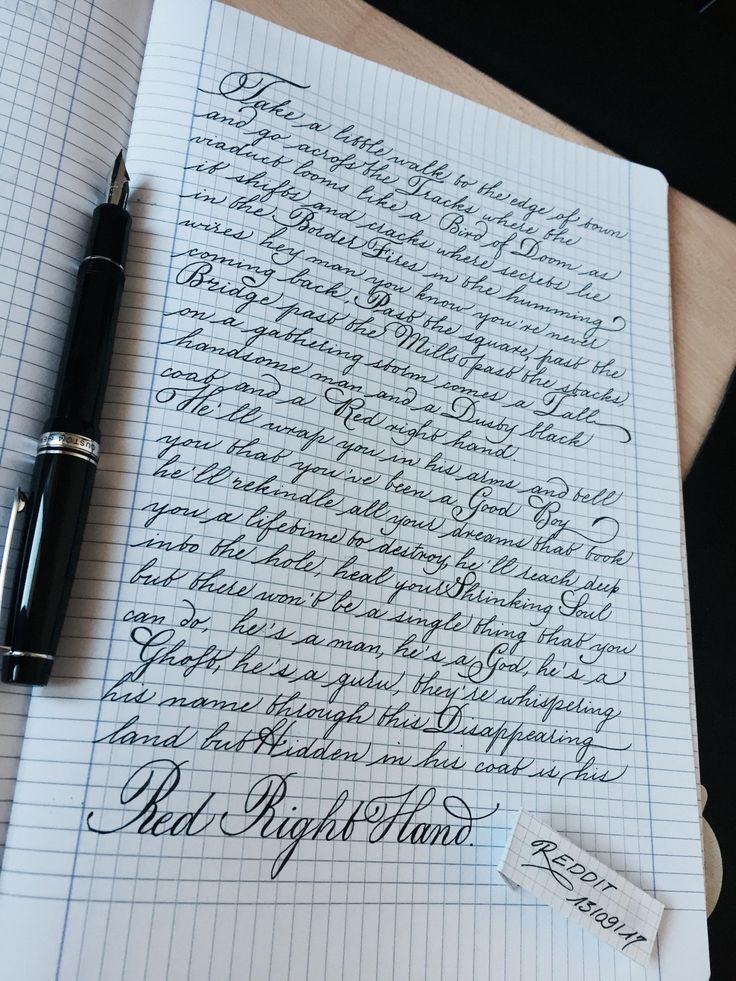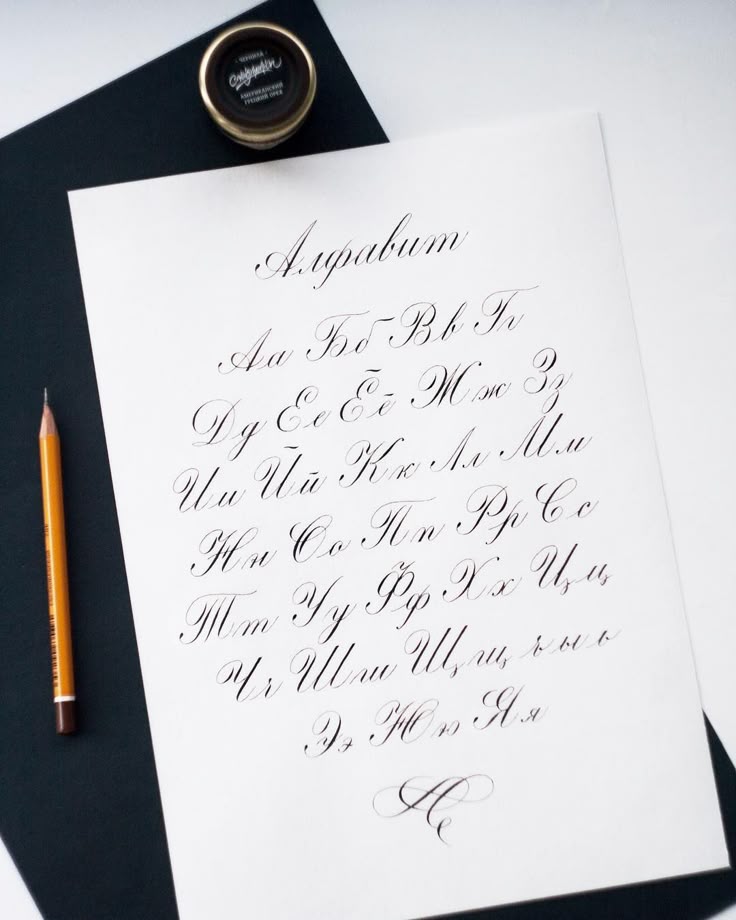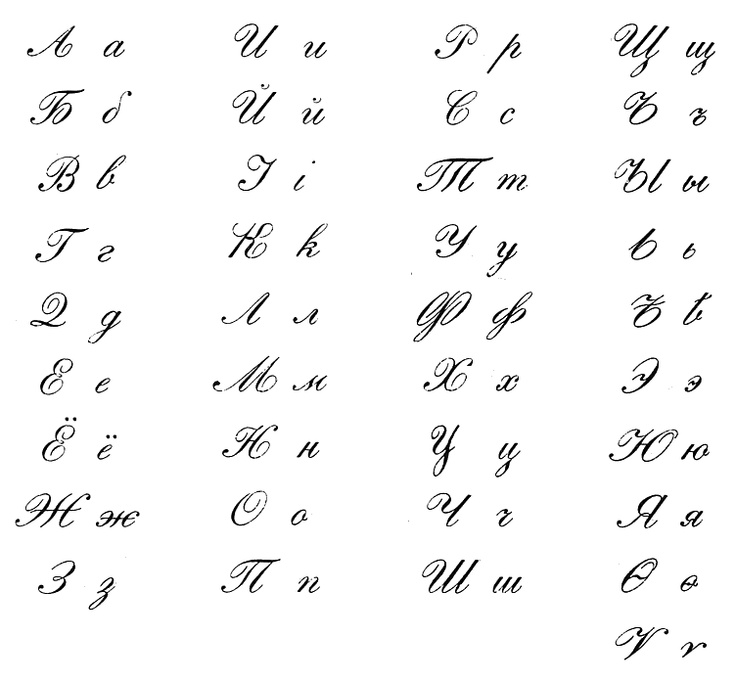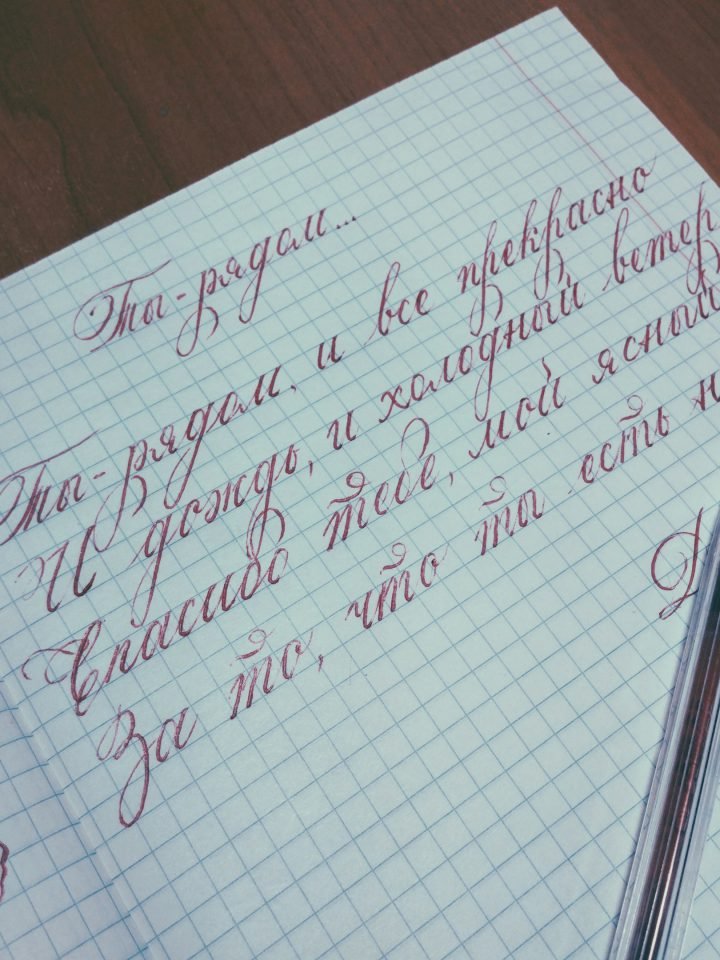
Красивый почерк онлайн: как научиться красиво писать
С появление смартфонов и социальных сетей мы все меньше стали уделять внимания письмам, написанным от руки. И совершенно зря. Ведь между мелкой моторикой рук и активностью нейронов головного мозга есть прямая связь: чем меньше пишет человек от руки, тем «ленивее» становится его мозг. Поэтому занятие выведения букв на бумаге может быть очень полезно для здоровья.
И плохой почерк – не причина отказываться от написания текстов. Учиться писать красиво можно и нужно в любом возрасте. Никогда не поздно освоить навыки чистописания. Есть много простых упражнений для этого. Можно научиться красивому почерку и онлайн – с помощью специальных компьютерных программ. Это интересно и увлекательно.
Каллиграфия что это такое?
Каллиграфия – это искусство красиво писать. Оно объединило в себе функции письма и рисунка. Суть техники состоит в увеличении эстетичности надписей путем добавления к буквам дополнительных элементов: штрихов, крючков, завитков, хвостиков, плавных и ломаных линий, угловатостей.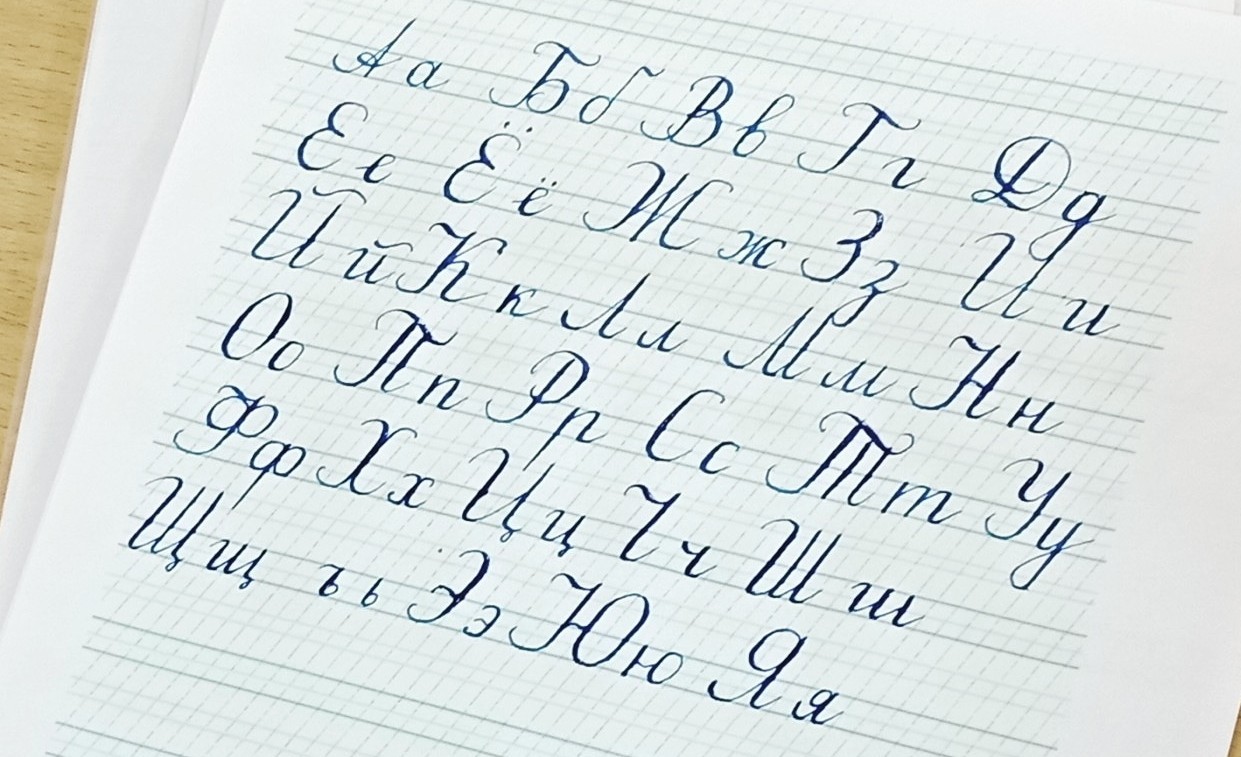
Развитие каллиграфии тесно связано с развитием письменности. Первые письменные знаки высекали на камнях, вырезали на деревянных дощечках, выдавливали палочкой на глиняных табличках.
Первое перо для письма было сделано из тростника. Позже появились гусиные перья. А два столетия назад появилось стальное перо.
Различают несколько основных видов каллиграфии:
Восточноазиатская | Зародилось искусство в Китае, Японии, Корее. |
Западноевропейская | Направление развилось на базе греко-римского письма. Классические образцы, используемые в наши дни, зародились еще в античности. |
Стиль возник на базе копирования священной книги мусульман Корана. Был выработан целый ряд канонических почерков. |
Сейчас основными каллиграфическими инструментами являются бумага, перо и тушь. Также для красивого письма используются авторучки, акварель, пастель, маркеры, чернила, уголь и многое другое.
Зачем нужно учиться красиво писать
Сейчас навыкам красивого письма отводится мало внимания. С появлением гаджетов отпадает необходимость писать от руки. Это имеет свои негативные последствия для здоровья.
В восточных странах, где придается большое значение нетрадиционной медицине, искусству письма отводится особая роль.
Например, руководители некоторых японских компаний специально приглашают учителей по каллиграфии для того, чтобы сотрудники в обеденный перерыв могли тренировать навык ручного письма. Считается, что это повышает творческий потенциал работников организации, учит их мыслить креативно.
Помимо пользы для здоровья есть много и других причин научиться писать красиво. Причем важно это как для детей, так и для взрослых.
Каллиграфия для детей
Почерк у ребенка формируется во время его обучения в начальных классах школы. Очень важно изначально уделять должное внимание формированию полезного навыка красивого письма у детей. Ведь от этого напрямую зависит успеваемость ребенка.
Неразборчивый почерк часто становится причиной плохих оценок в школе. За небрежное написание отметки снижаются. Это негативно сказывается на мотивации ребенка к получению новых знаний. Интерес к учебе пропадает. Как результат этого – формирование пониженной самооценки у детей.
Занятия каллиграфией способствуют коррекции почерка у школьников. Кроме того, они помогают выработать у детей усидчивость и терпение – качества, необходимые при освоении школьной программы. А развитие мелкой моторики рук при написании слов положительно влияет на активизацию процессов в головном мозге.
Каллиграфия для взрослых
Считается, что почерк может многое рассказать о внутреннем состоянии человека. Неровные строчки, буквы разной величины, неразборчивые записи выдают сильное внутреннее волнение и переживания обладателя такого почерка.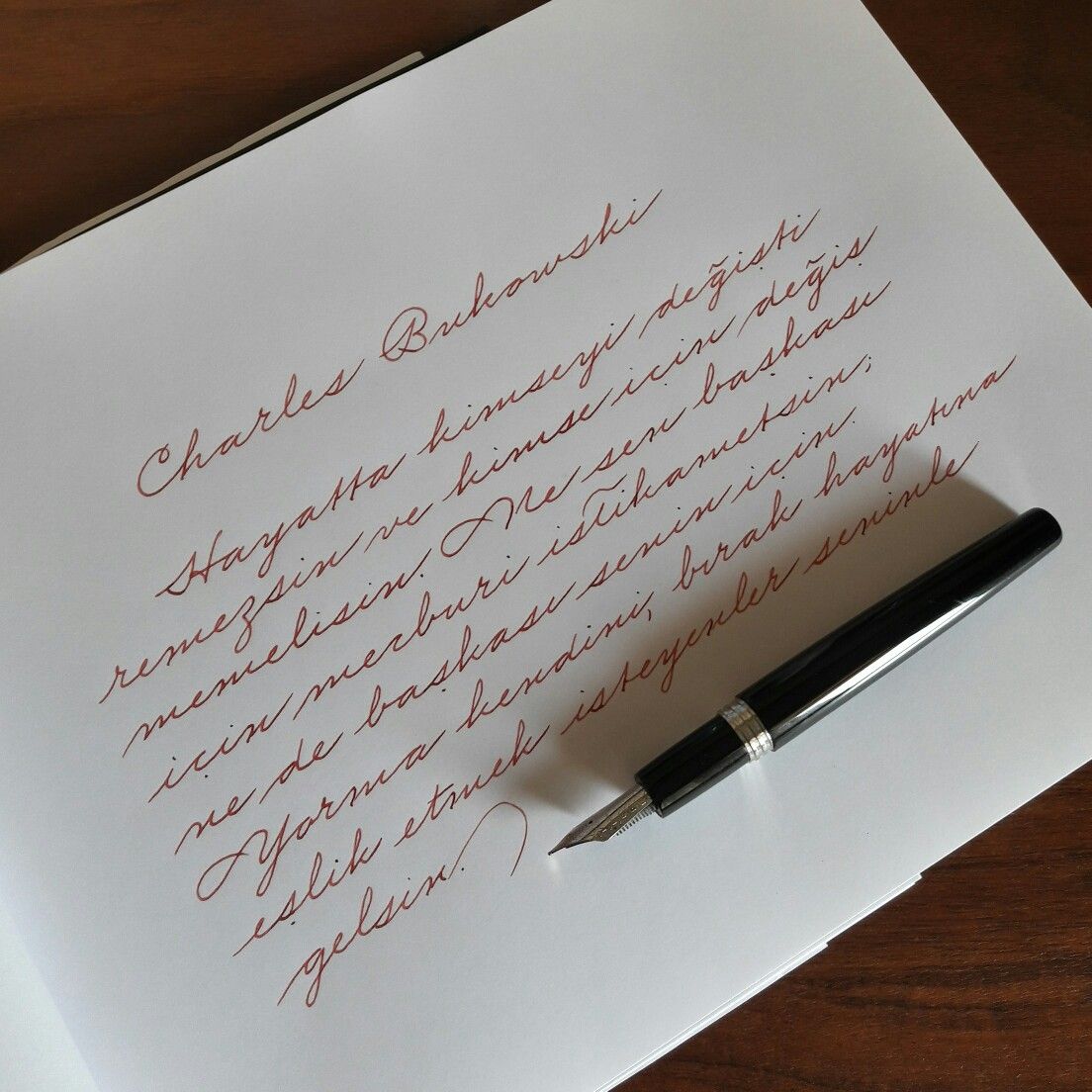
Психологи уверены, что процесс Эмоция – Действие может быть и обратным, то есть Действие – Эмоция.
Другими словами, если человек быстро и неразборчиво пишет потому, что сильно взволнован, то успокоиться ему поможет медленное и аккуратное написание букв. Занятия каллиграфией помогают стабилизировать эмоциональный фон и выработать стрессовоустойчивость и уверенность в себе.
Помимо пользы для психического здоровья можно назвать как минимум 3 причины для того, чтобы попытаться исправить небрежный почерк во взрослом состоянии. Занятия каллиграфией способствуют:
- Тренировке мелкой моторики. Это стимулирует работу отделов мозга, отвечающих за логическое мышление и воображение.
- Выработке красивого почерка. Письмо, написанное аккуратно, позволяет произвести хорошее впечатление, расположить к себе людей, вызвать у них доверие.
- Приведению некоторых физических показателей в норму. Отмечено, что во время кропотливых занятий написания букв снижается кровяное давление, замедляется пульс, нормализуется дыхание.